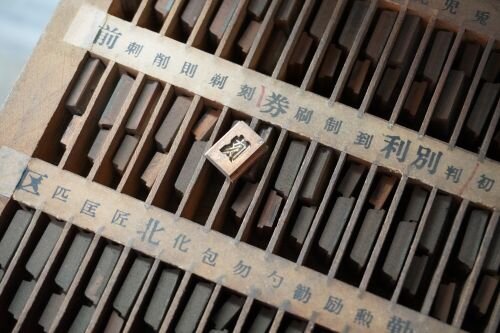
ワールドワイド活版印刷 Worldwide Kappan
活版印刷をめぐる旅に出ましょう。
世界にはまだ、活字を鋳造して版を組み、本を作っている工房があります。貴重な設備を大切に保存し、次の世代に残すために活動している人たちもたくさんいます。
どこに? どれくらい残っているの?
本展では、世界各地で活版印刷を支える人びと──活字を作り続ける鋳造所、1文字ずつ活字を並べて印刷し、書籍を制作する印刷所、それらの技術と知識を次代へ伝える文化施設──を紹介します。
鉛合金による金属活字を使った活版印刷は、15世紀半ばに現在のドイツ・マインツでグーテンベルクによって確立され、長い時間をかけて世界中に広まっていきました。遠い東の果て、日本でその技術が根付いたのは19世紀になってから。それぞれの国の言語や文字、それまでの印刷文化のあり方によって、活版印刷の受容と定着のかたちは大きく異なります。
活版印刷が印刷の主流ではなくなった今もなお、世界各地で、その技術と設備を未来へつなごうとする活動は続いています。
2026年、市谷の杜 本と活字館は開館5周年、大日本印刷(DNP)は創業150周年を迎えました。1876年に日本で活版印刷所として誕生した会社が、その150年後の節目の年に、世界の活版印刷の現在をご案内いたします。
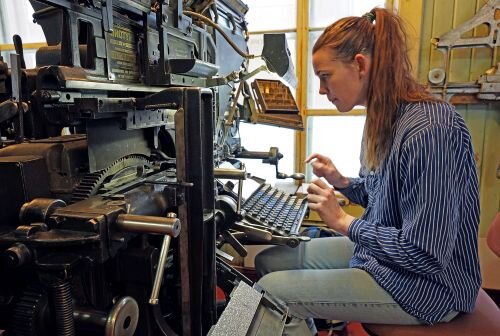
LINOTYPE鋳造の様子(Fjeld-Ljoms・ノルウェー)
宋朝体の母型(築地活字・日本)